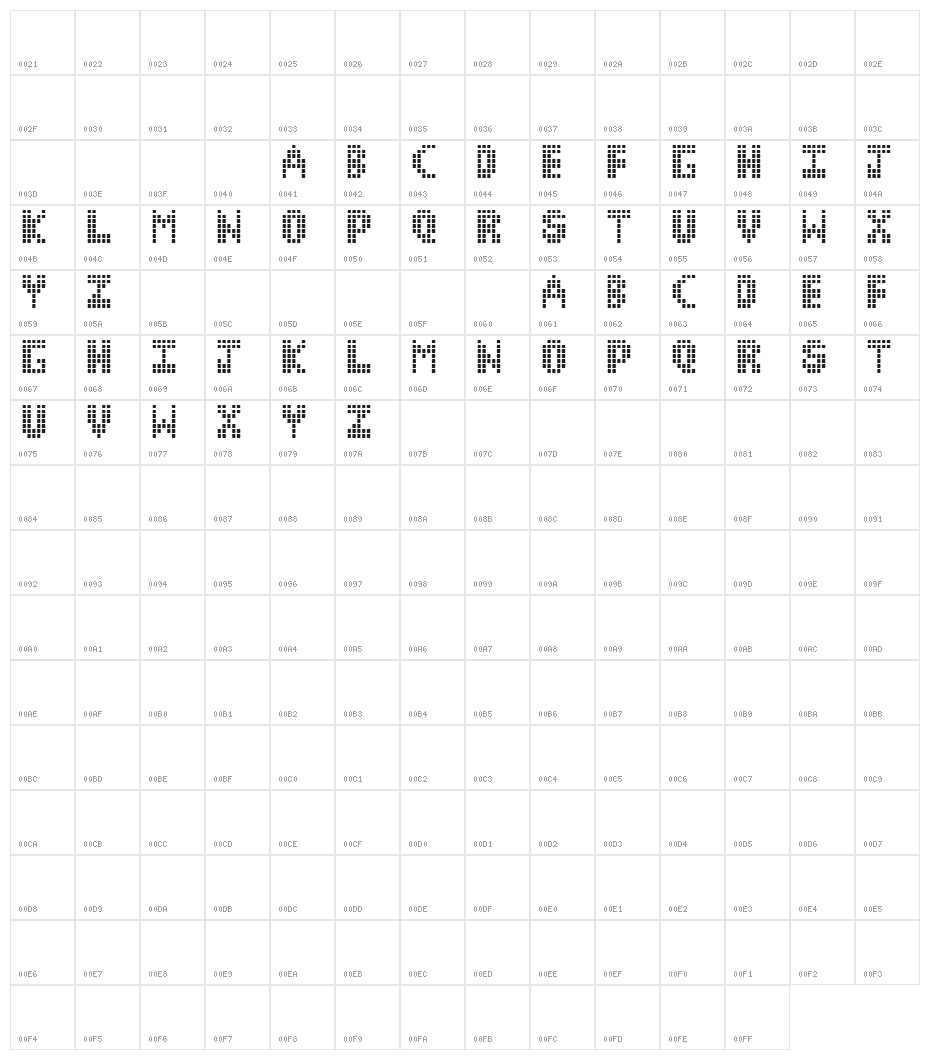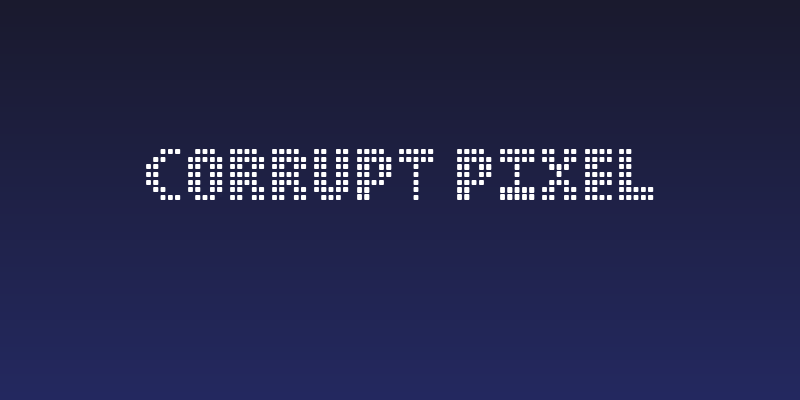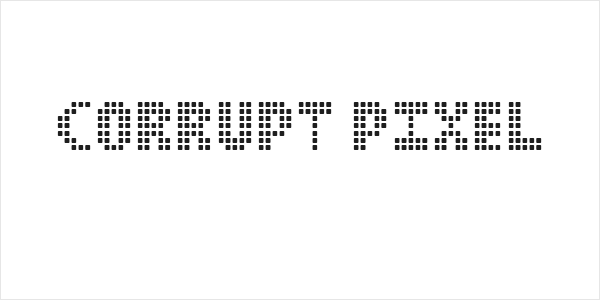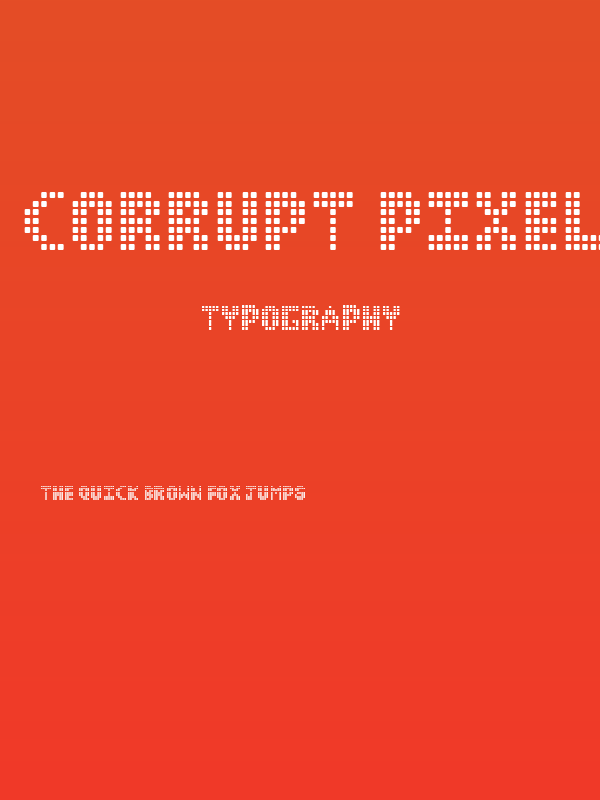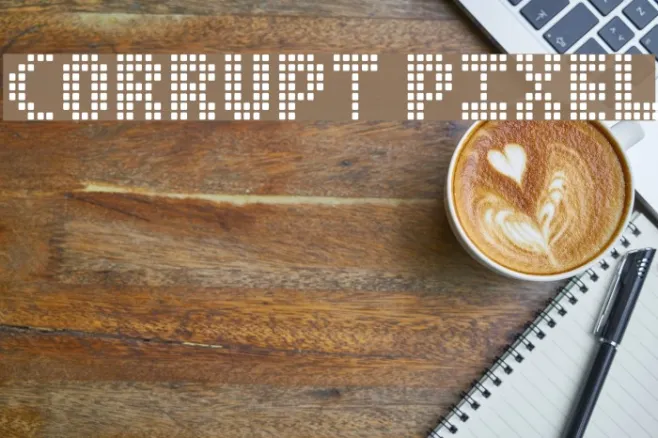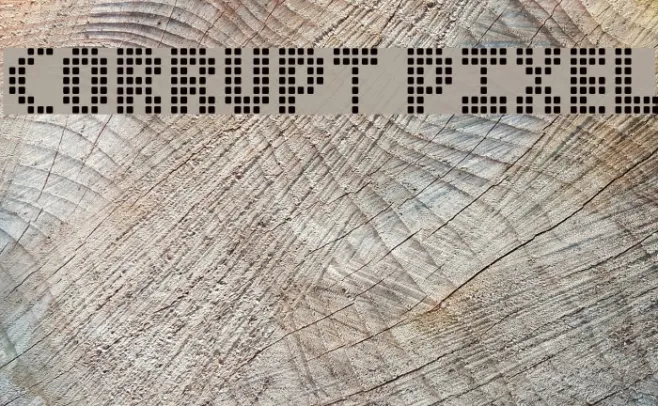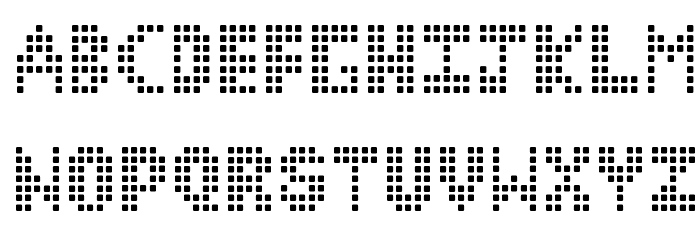
Corrupt Pixel Font
| Progetti proposti | Ideal for retro video game graphics, digital-themed posters, tech event branding, and nostalgic merchandise designs. |